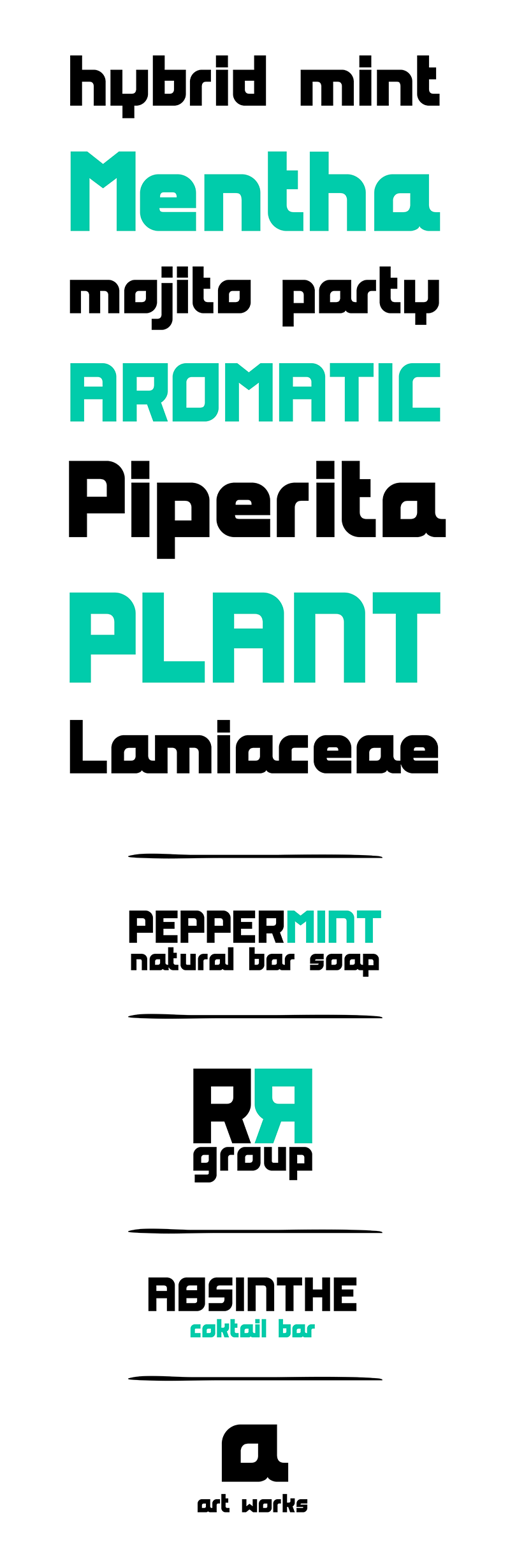
Peppermint é uma fonte Display Square Sans Serif que oferece uma experiência única no mundo das letras digitais. A agressividade dos ângulos contrasta harmoniosamente com a suavidade das curvas, criando uma interação dinâmica entre os diferentes elementos da tipografia. Em algumas palavras, o Peppermint pode ser vista como um veículo que leva você em uma viagem pelos desafios e descobertas de cada letra. A fonte retrata vividamente essa ideia ao mostrar suas folhas no ar acentuando letras específicas como “a”, “o” ou “Q”. É uma fonte Display fresca, ideal para ilustrar gráficos inovadores. Seja em design editorial ou aplicativo, Peppermint traz vida e movimento às páginas e projetos que usam essa linda fonte.